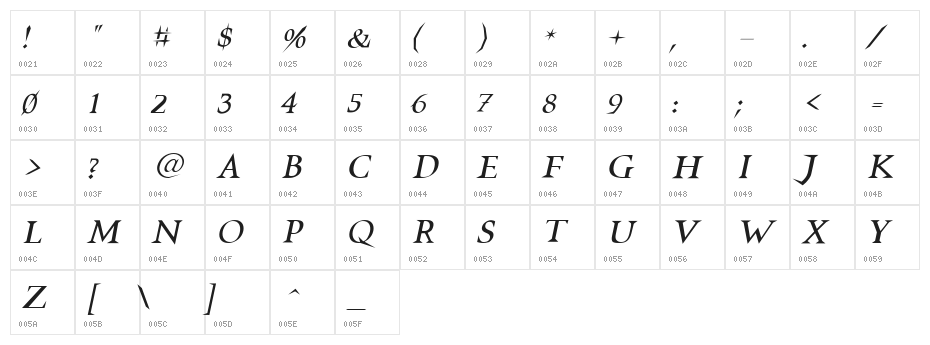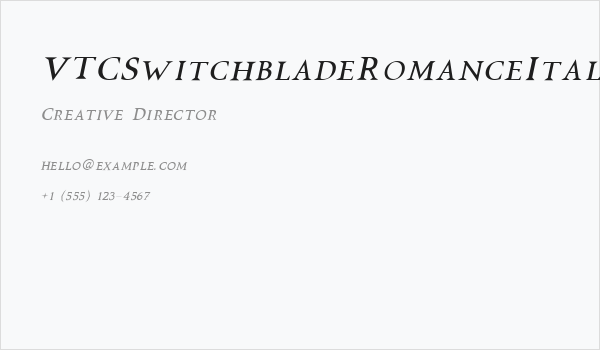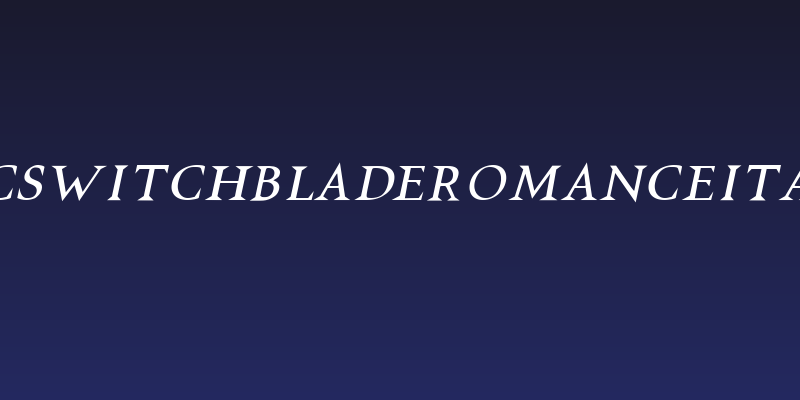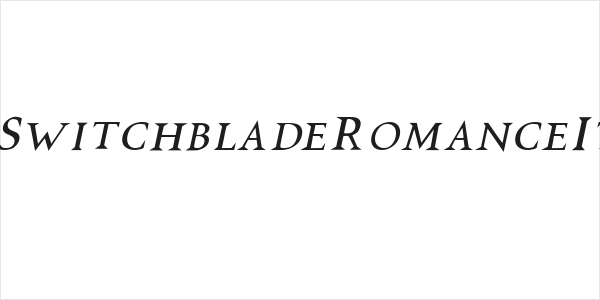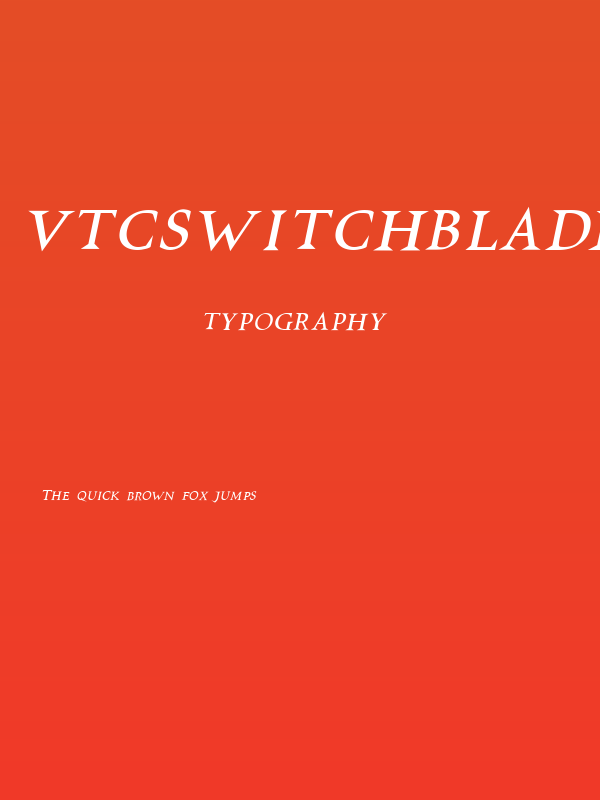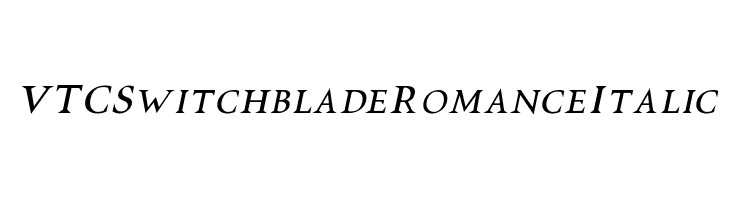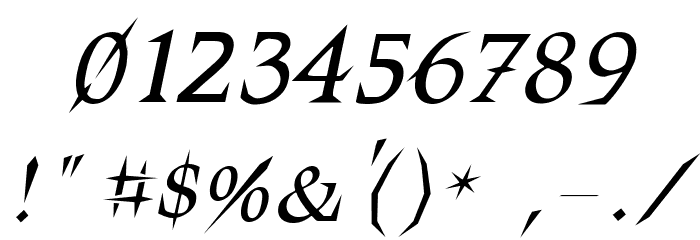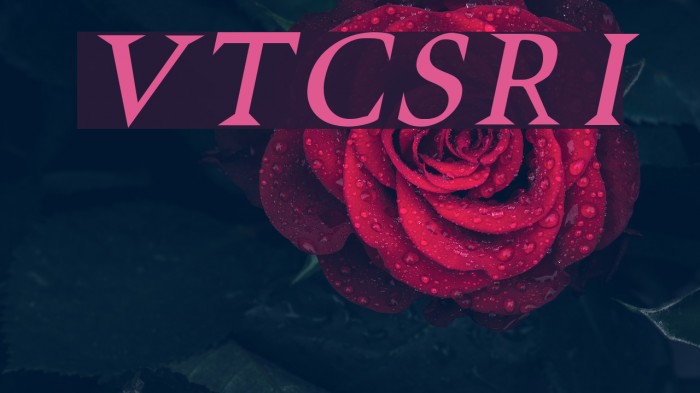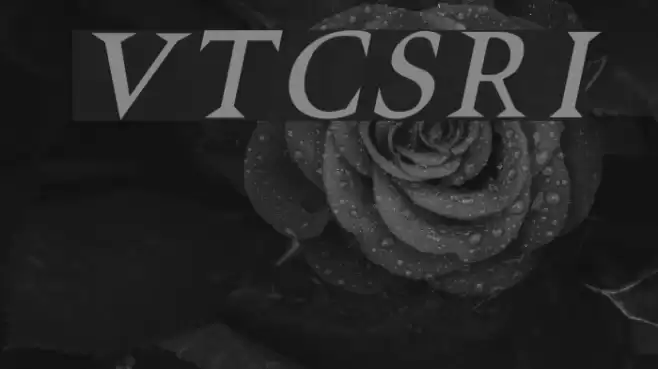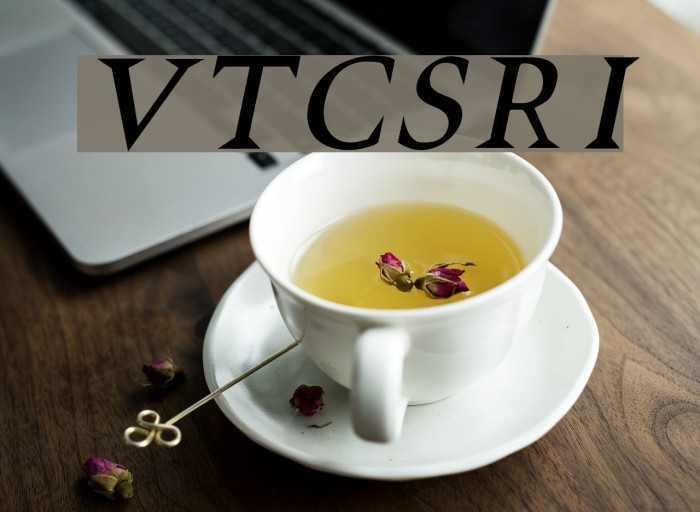
VTCSwitchbladeRomanceItalic Font
| Vorgeschlagene Projekte | Ideal for movie posters, album covers, branding for edgy or modern products, and any design requiring a bold statement. |